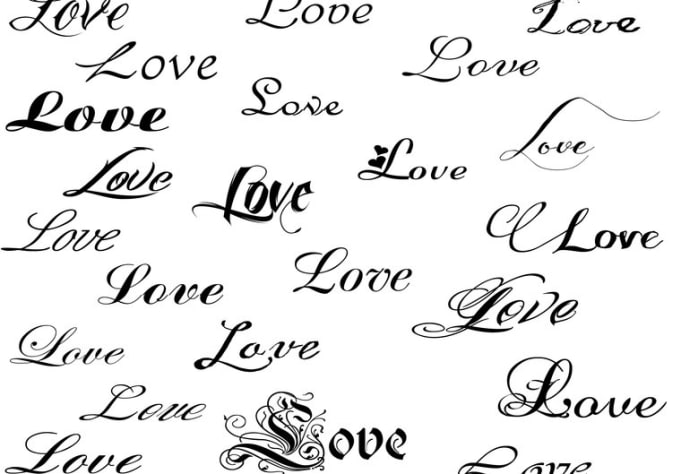
Одним из самых распространенных стилей тату-индустрии является нанесение какого-либо текста.
Выбор текста – вопрос непростой, но еще более сложным будет выбор самого шрифта. Учитывая целое море вариантов, а также индивидуальный подход мастера к каждому клиенту, можно долго рассуждать о конкретных типах тату.
Стиль шрифта
Как выбрать шрифт для тату?
Первым делом, если вы определились с текстом, нужно подобрать соответствующее оформление.
Кроме того, стоит учесть стиль самого клиента, что подойдет под его стиль, хобби, работу, жизненные ценности. Исходя из множества деталей можно определить наилучший вариант. Заметим, что у нас можно просмотреть все тату шрифты онлайн, а также получить справку и консультацию от онлайн-консультанта. Для этого необходимо зайти в соответствующую категорию и рассмотреть предлагаемые варианты. Вы также можете изучить сотни других вариантов в сети, прикинуть, как тату будет смотреться на месте, на которое вы собираетесь наносить его.
Размер шрифта
Чтобы определиться с размером шрифта нужно определить точное размещение текста. Расположив его, можно представить другие варианты размеров – ширины и длины каждой буквы. Текст может состоять как со строчных букв, так и начинаться с заглавной, выделяя имя или город, страну.
Цвет надписи
Если вы рассмотрели тату шрифты и определились с вариантом, а также уверены в тематике надписи, можно рассмотреть палитру цветов.
Возможно, наилучшим вариантом будет черно-белая татуировка или же актуальнее будет сделать тату в ярких цветах. Можно сделать несколько цветов, комбинируя их:
- Сделать яркую обводку.
- Добавить цветную тень.
- Заполнение букв может быть с цветовыми переходами.
Тату шрифты от наших мастеров
Это оптимальный вариант для получения желаемого результата. Выбранные на сайте шрифты онлайн, отобраны как наилучшие и наиболее удачные для практически любых мест нанесения. Стиль самого тату может быть как минимализм, так и готика или графика. Вы сами выбираете наилучший стиль для своего тату, однако совет мастера всегда будет полезен. Рассмотрите тату шрифты у нас, подумайте об оформлении, выберите несколько вариантов и продумайте заранее все детали.![]()
Язык надписи
Немаловажным фактором является выбранный язык для татуировки.
Исходя из выбора, нужно прикинуть шрифт, так как не каждый из них хорошо смотрится на том или другом языке. Для понимания, пропишите надпись, которую собираетесь набивать, чтобы рассмотреть все преимущества и недостатки того или другого шрифта.
Популярные места для татуировки
Место для тату – выбор клиента, однако есть популярные места для нанесения шрифтов.
Такими местами можно считать предплечья рук, ноги, часто встречаются надписи на запястьях, шее, спине. Многие клиенты рассматривают тату шрифты для выполнения на груди, вроде порядкового номера или имени любимого человека.
Предпочтения в шрифтах
Девушки больше любят утонченность, изысканность линий, тонкие и легкие шрифты.
Если говорить о мужском поле, то предпочтение отдается более крупным, жирным и строгим надписям, большинство из которых имеют обводку, возможно цветную.
Однако, эти стандарты не всегда подходят под наших клиентов, учитывая, что большинство из них – люди с яркой внешностью и хорошим вкусом.
Цены на татуировки-шрифты
Стоимость татуировки напрямую зависит от размера букв, длины надписи и сложности самого шрифта.
Также она будет варьироваться от количества цветов, использованных для выполнения работы. Более подробную информацию Вы можете получить непосредственно в салоне, у выбранного мастера. Цены на тату шрифты у разных мастеров могут отличаться, что зависит от опыта и оценки татуировщиком заказа.
Подобрать шрифт для тату онлайн
В конструкторе вы можете выбрать цвет, написать свою фразу, сделать пробный вариант татуировки. Данный конструктор является. примером. Подберите варианты для тату фраз. Так же можете поэкспериментировать с буквами, выбор и значение которых можно найти в интернете.
Использовать при подборе стоит те шрифты которые больше всего лежат к вашей душе.
Тату с надписями распространены среди людей старшего возраста, молодежи. Если есть желание набить такое тату, то обязательно надо разобраться в тонкостях и разновидностях таких изображений.